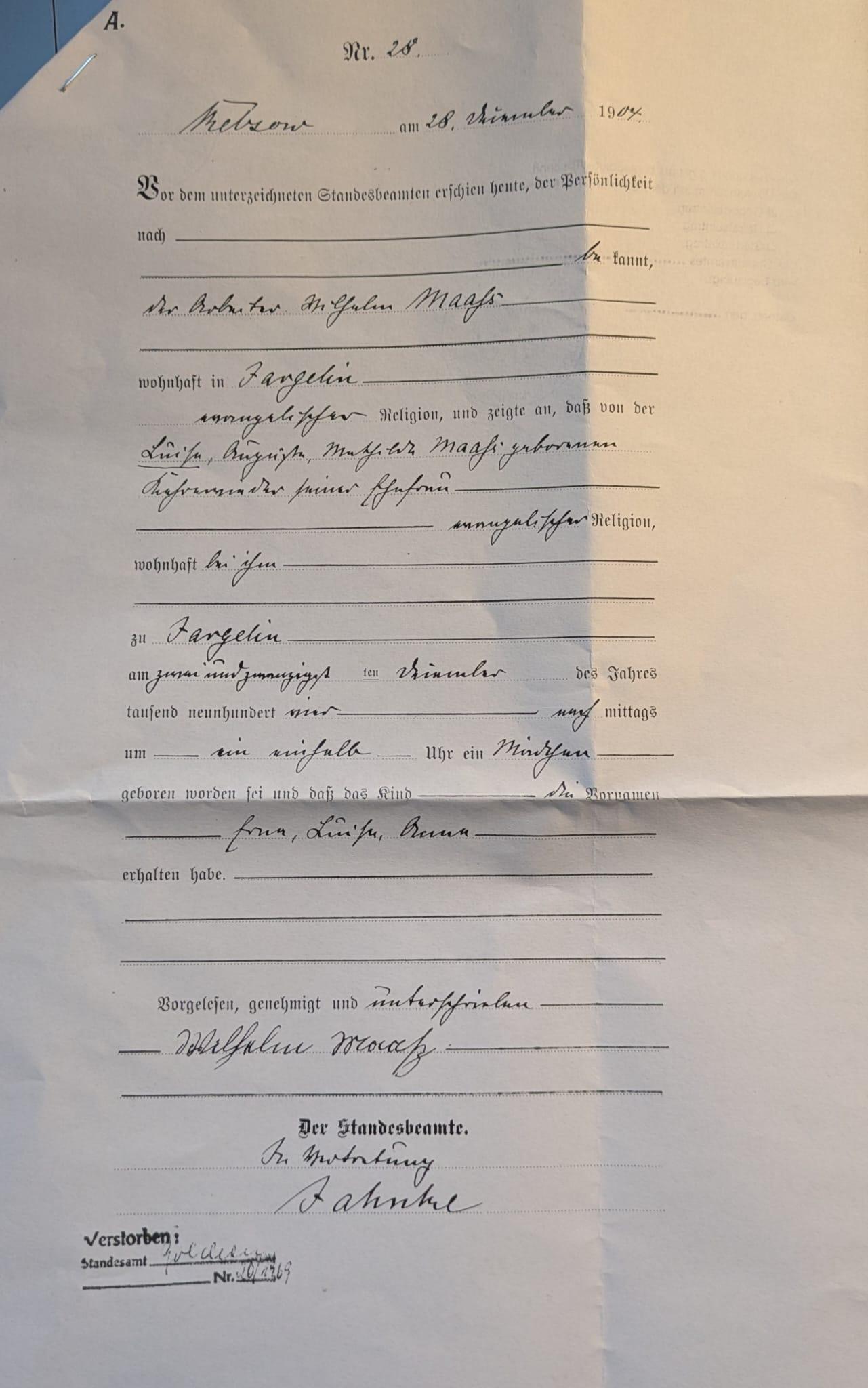
Geburtsurkunde 1904 / Bitte um Hilfe beim Entziffern
ich bin ganz neu hier. Ich beschäftige mich seit einiger Zeit mit dem Thema Ahnenforschung und habe nun eine Geburtsurkunde bekommen, bei der ich nicht alles eindeutig entziffern kann. Vielleicht hilft mir jemand. Ich würde mich sehr freuen.
Vielleicht hilft mir jemand.
Was genau kannst Du nicht entziffern?
Nr. 28
Relzow (?) am 28. Dezember 1904
(...) bekannt, der Arbeiter Wilhelm Maaß wohnhaft in Jargelin
evangelischer Religion, und zeigte an, dass von der Luise Auguste Mathilde Maaß (?)
geborene ... ?
Name des Kindes:
Erna Luisa Anna ?
Ein Ort Melzow gibt es leider nicht in der Region. Deshalb bin ich davon ausgegangen, dass es sich um kein M handeln kann. Kann jemand vielleicht entziffern was hinter dem Namen der Mutter steht? ...geborene... Alles was dananch kommt kann ich überhaupt nicht zuordnen.
Kann jemand vielleicht entziffern was hinter dem Namen der Mutter steht? ...geborene...
Ich vermute, es heißt: geborenen Kehrewieder. Und natürlich: seiner Ehefrau.
Ich bin nicht sicher, ob es dieselbe Person ist, aber hier ist ein Ehepaar Maaß / Kehr(e)wieder gelistet. Zeit und Ort passen zum Dokument. Damit wäre auch die Lesart Relzow für den Ort bestätigt.
Beim Namen des Mädchens vermute ich Luise Anne, das a in Erna hat ja einen zusätzlichen Kringel.
Viel Dank für die Hilfe und den Link. Die Seite war mir bisher nicht bekannt. Mich wundert etwas, dass unter dem Link nicht die Tochter Erna Maaß aufgeführt ist aber ich werde weiter recherchieren und schauen ob es sich um die aufgeführten Personen handelt. Vielen Dank